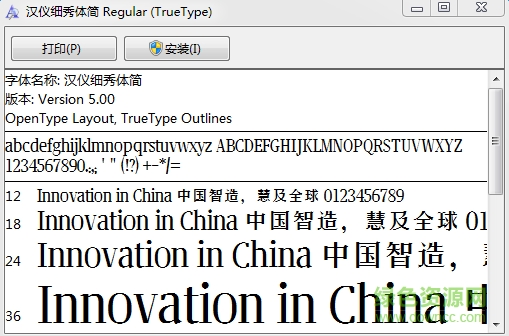
漢儀細(xì)秀體簡(jiǎn)
漢儀細(xì)秀體簡(jiǎn)是一種很規(guī)則的電腦簡(jiǎn)體字,這種字體就特別適合書(shū)本印刷、廣告設(shè)計(jì)等方面,因?yàn)閷?xiě)的字是很整齊、很工整的,所以大家如果需要這款字體的話,可以來(lái)綠色資源網(wǎng)下載。